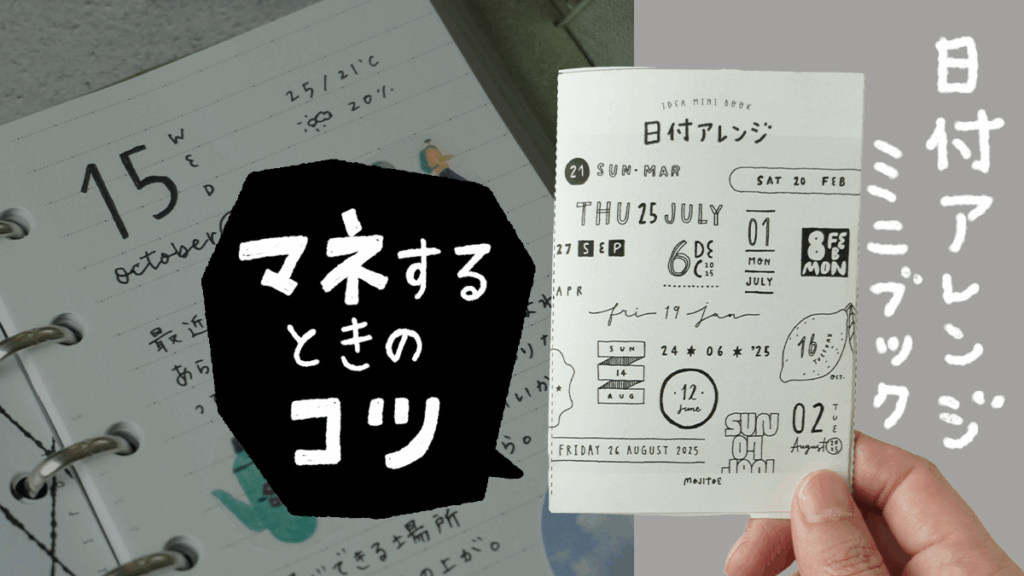
日付アレンジを真似するときのコツ
「かわいい日付アレンジを試してみたいけれど、いざ書くとバランスが悪くなってしまう…」そんなお悩みはありませんか?今回は、バランスを取りにくいデザインを例に、うまく書くコツ をご紹介します。 Contents アイデアブッ … 続きを読む 日付アレンジを真似するときのコツ